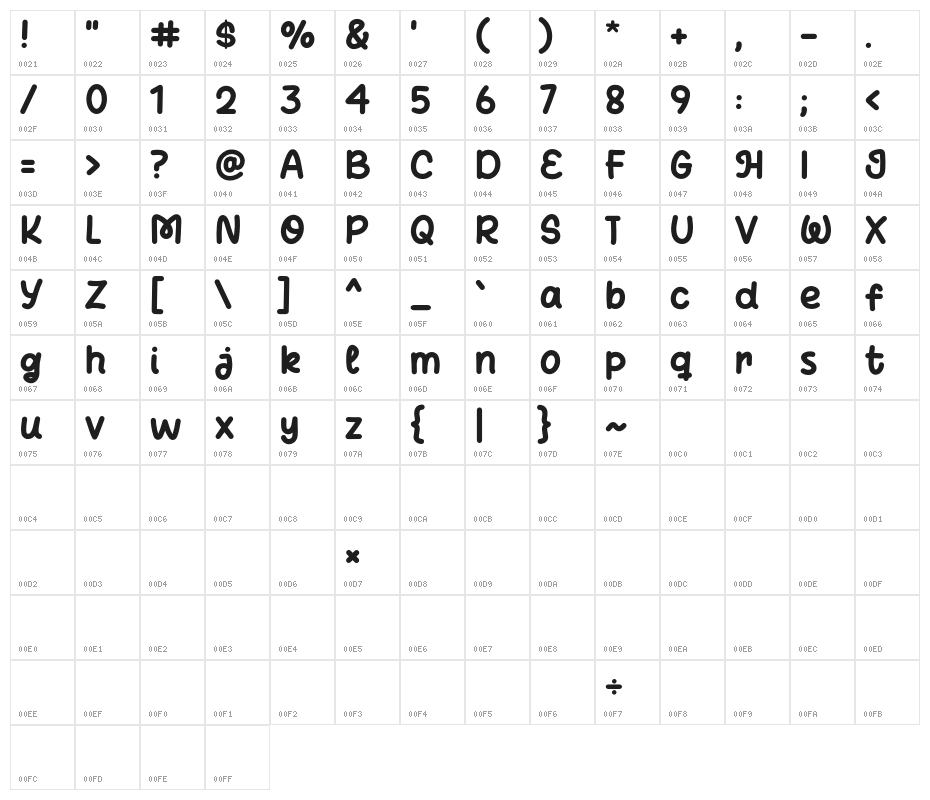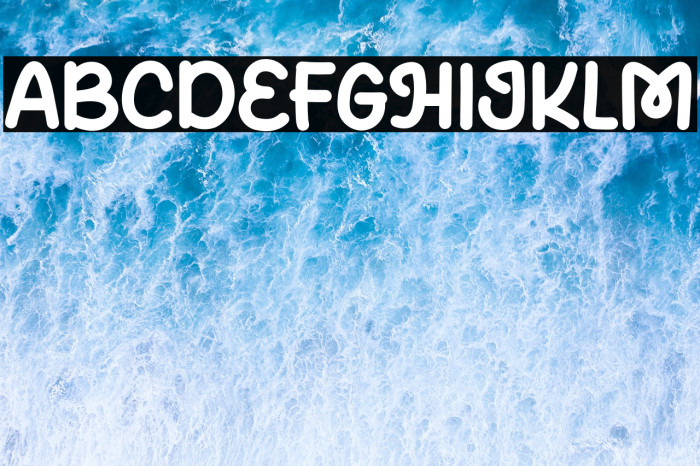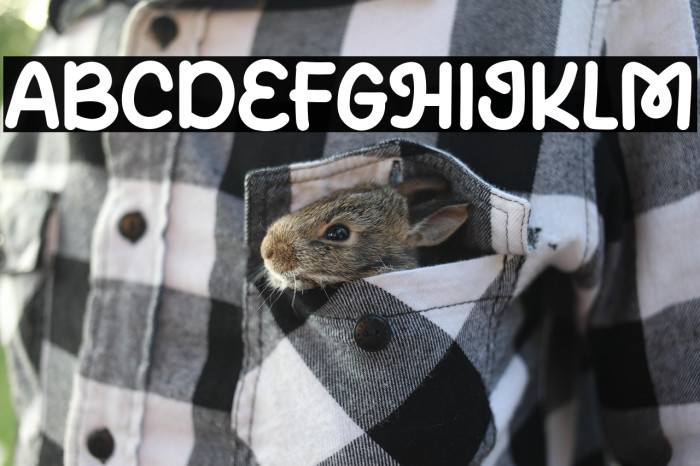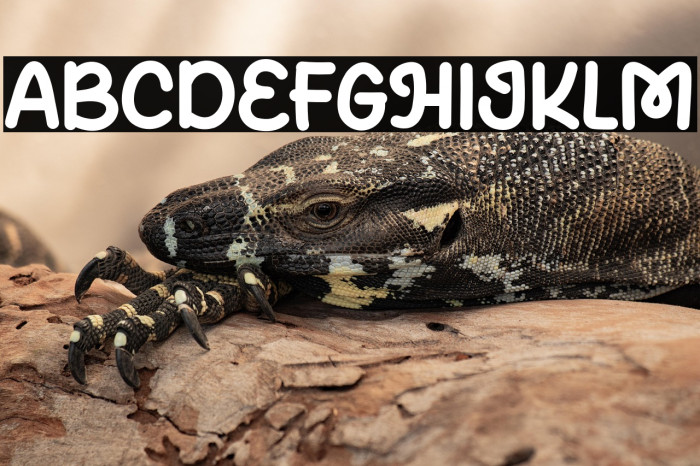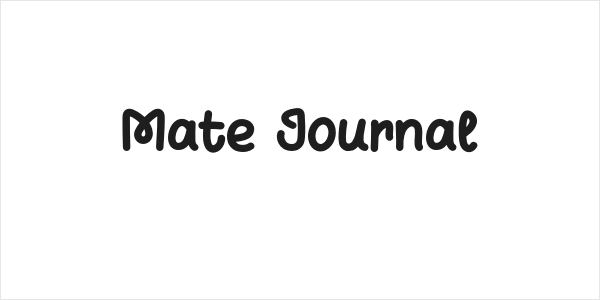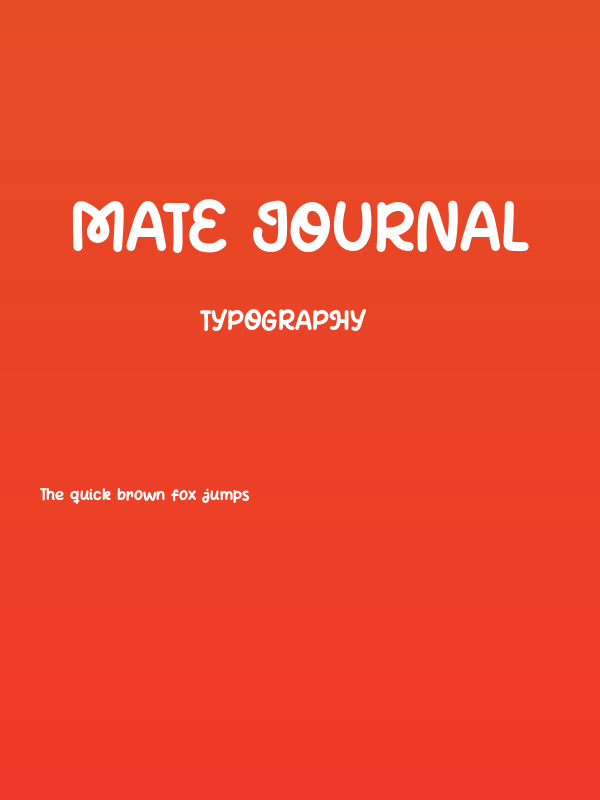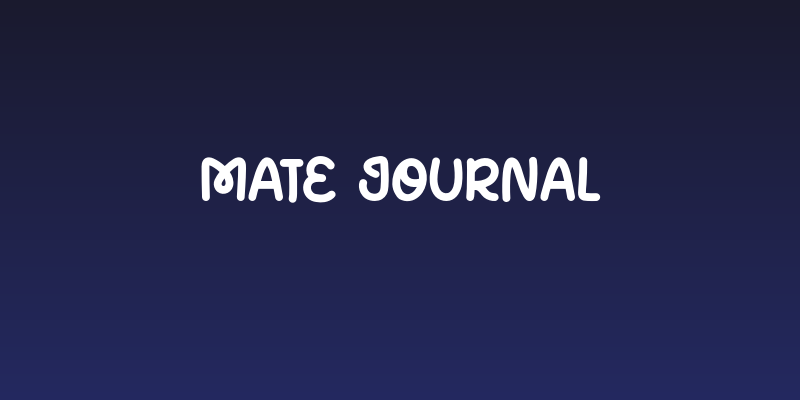
Mate Journal Font
| Gesamtstil | Playful |
| Vorgeschlagene Projekte | Ideal for children's books, playful branding, casual invitations, and creative posters. |